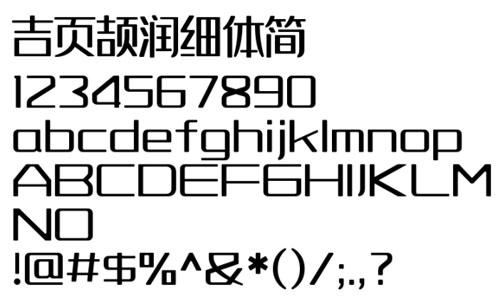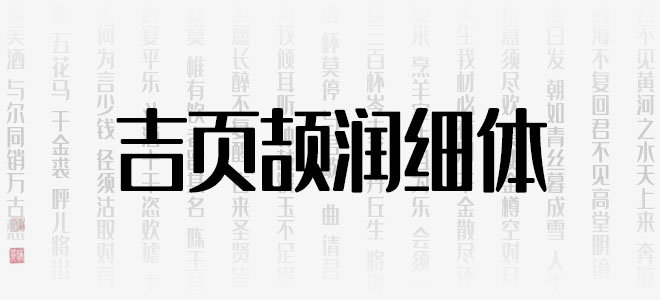
吉頁(yè)頡潤(rùn)細(xì)體簡(jiǎn)字體是一款由吉頁(yè)字庫(kù)推出的藝術(shù)字體,字體非常漂亮,除應(yīng)用于綜藝之外,還可適應(yīng)于海報(bào) / 畫(huà)冊(cè) / 書(shū)籍 / 影視 / 廣告 / 游戲等領(lǐng)域,歡迎需要此字體的朋友前來(lái)下載使用。
吉頁(yè)頡潤(rùn)細(xì)體簡(jiǎn)字體